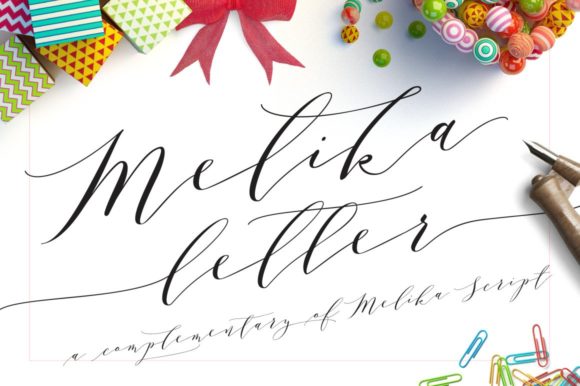
Melika Letter
Trouver les bons éléments de conception peut être un défi, mais Melika Letter propose une collection exceptionnelle qui rehausse instantanément votre travail.
Que vous créiez des produits POD (impression à la demande), des invitations de mariage ou des visuels pour les réseaux sociaux, Melika Letter est un choix idéal.